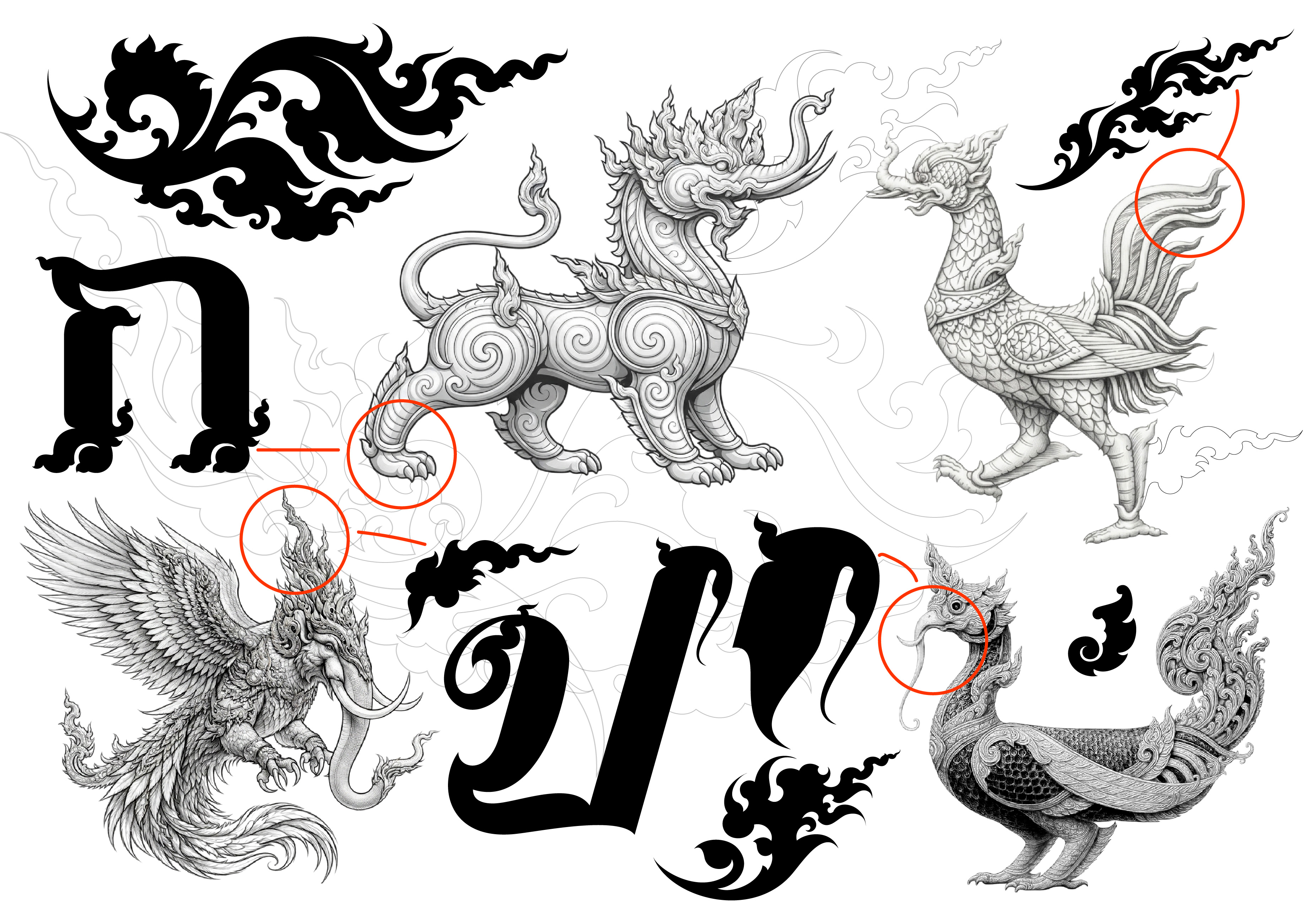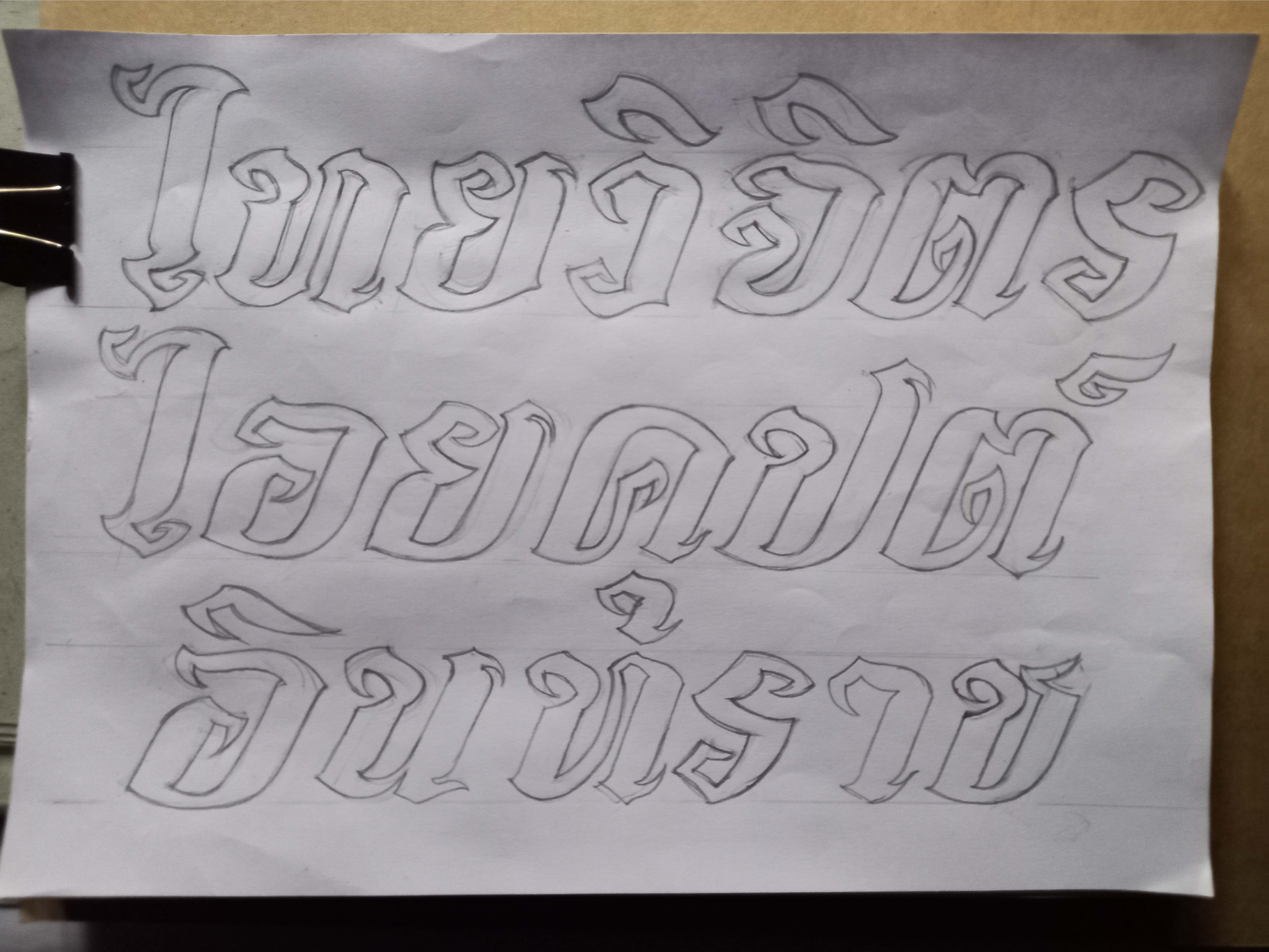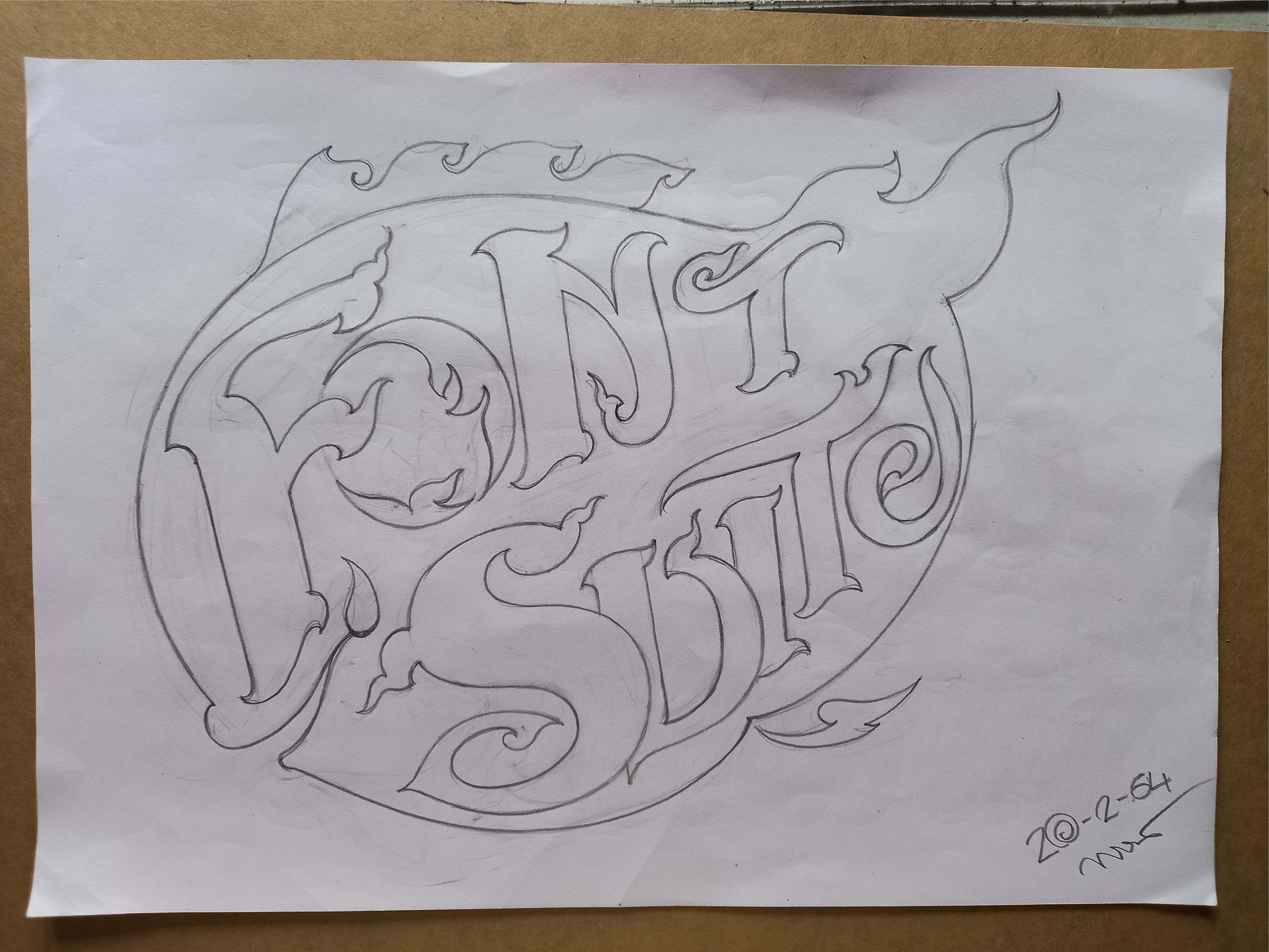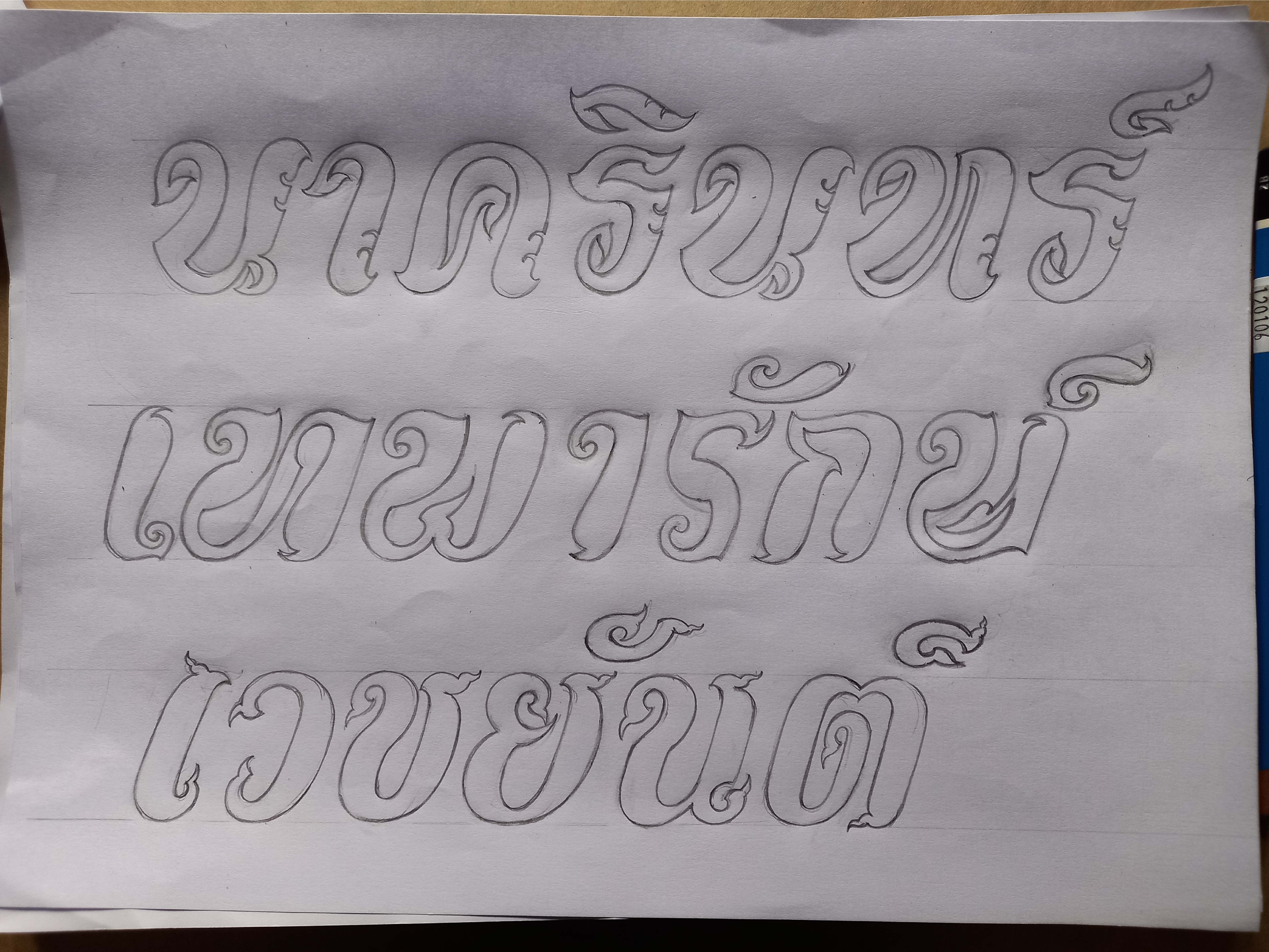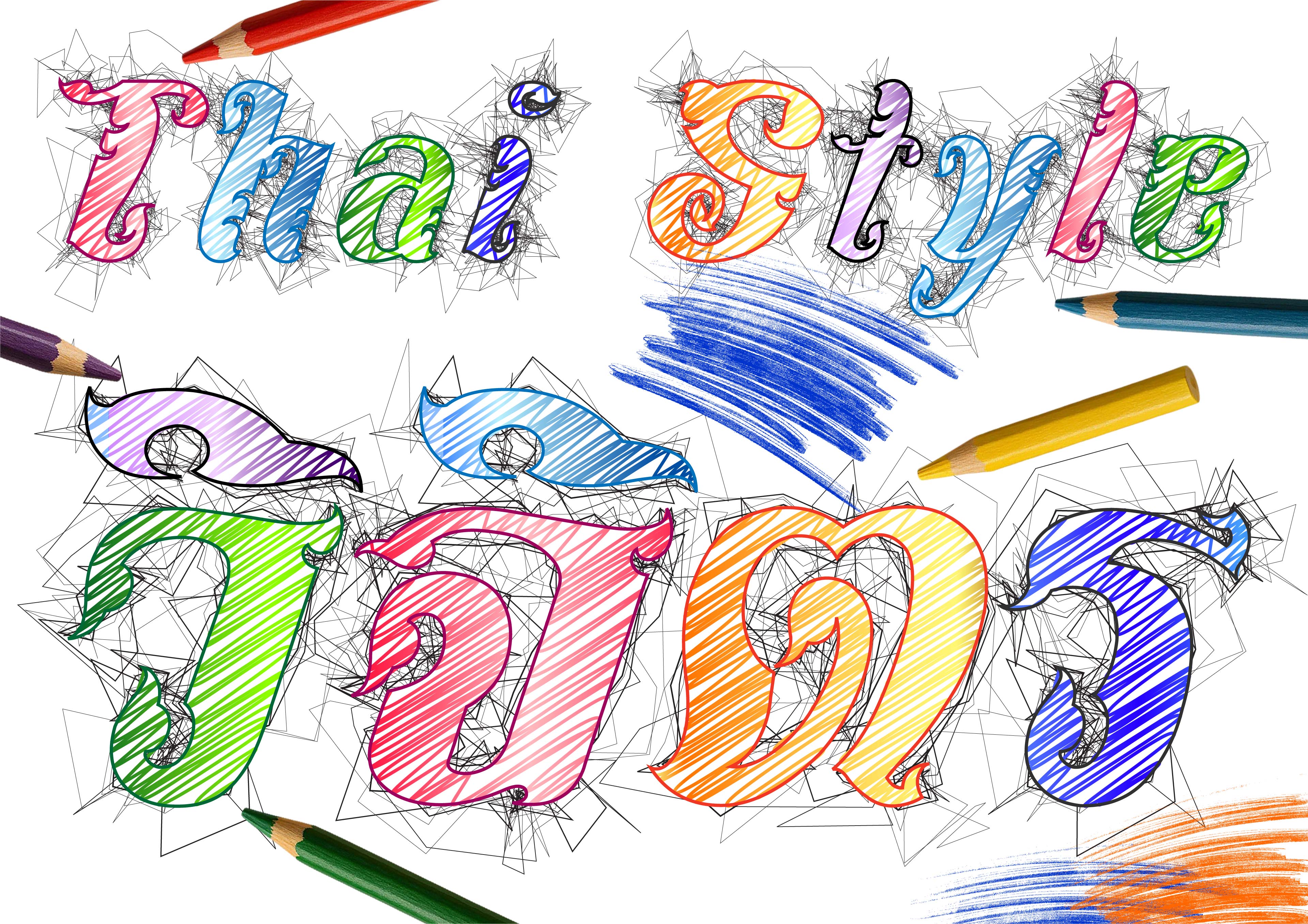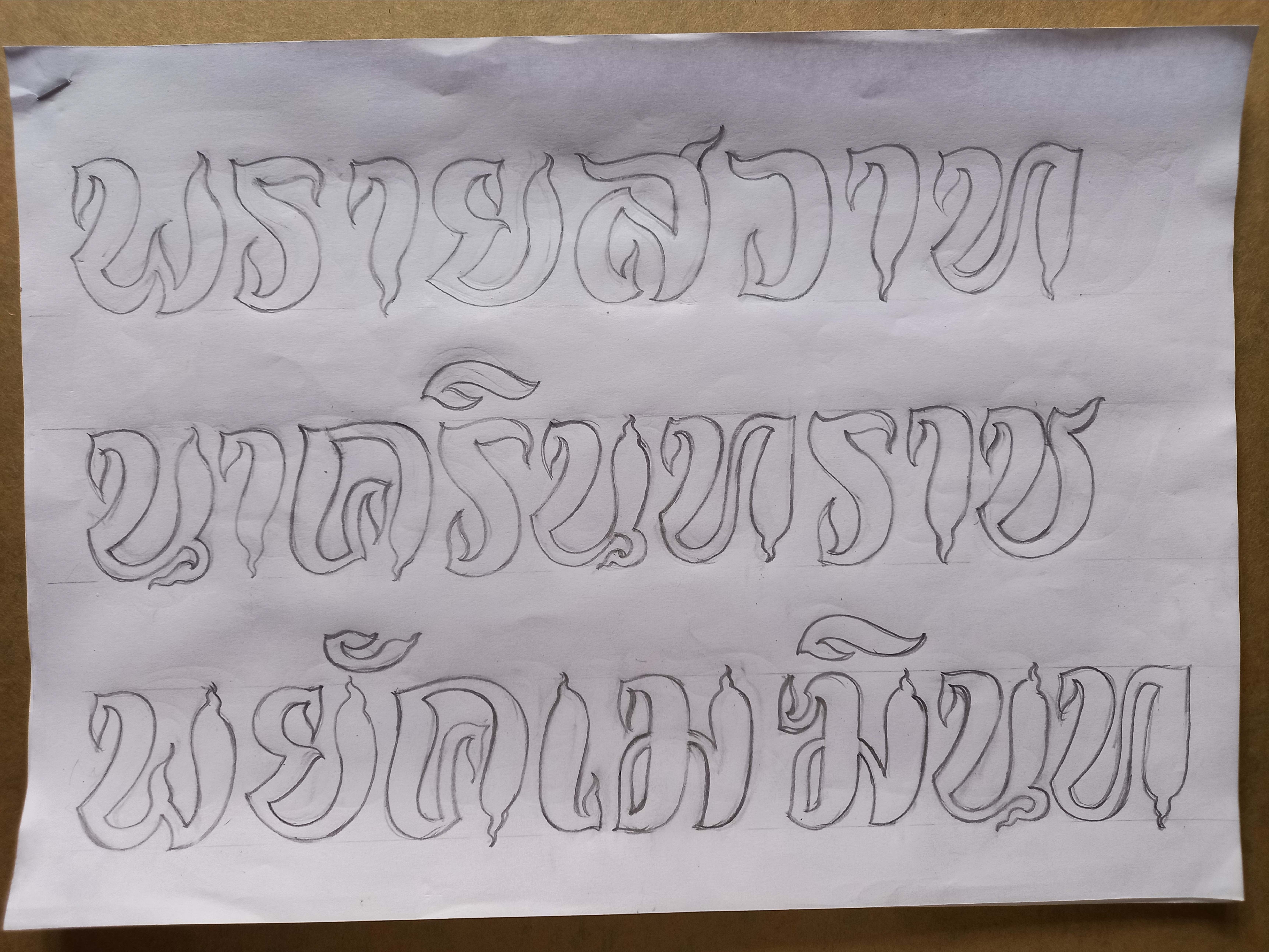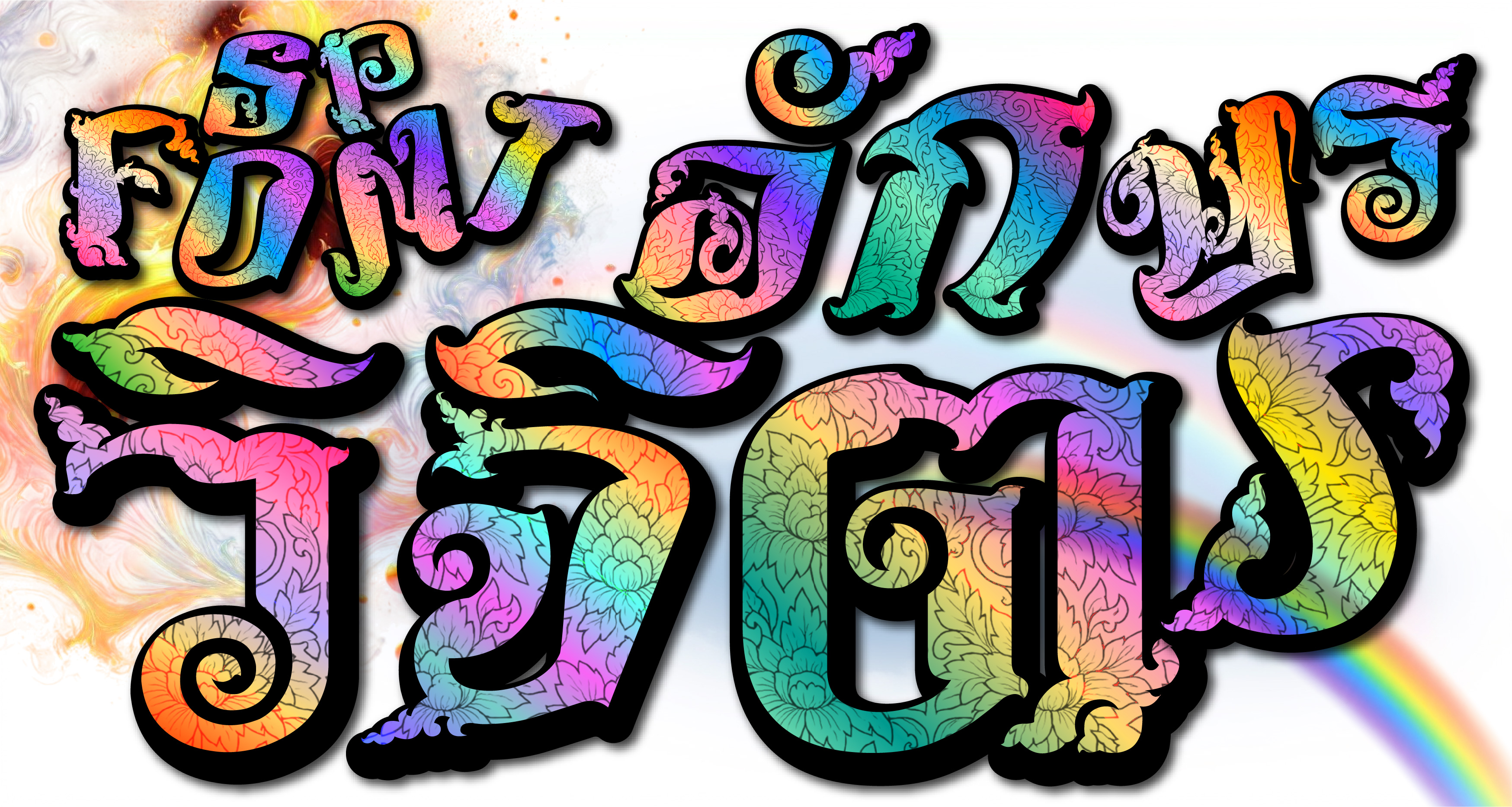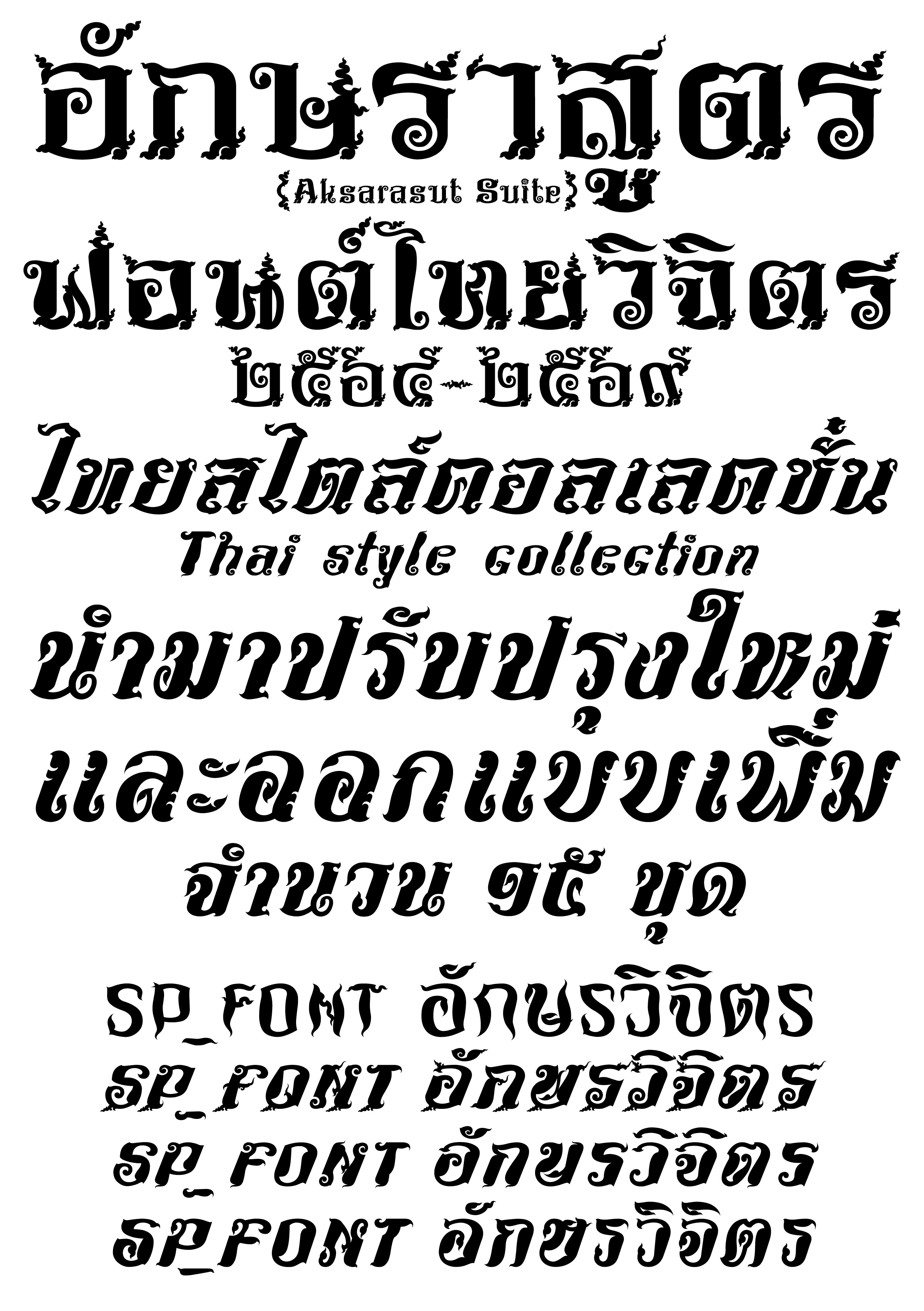
อักษราสูตรกับไทยวิจิตรฟอนต์
ไทยวิจิตรอักษราสูตร
จุดเริ่มต้นจากนกหัสดีลิงค์
นกหัสดีลิงค์ หรือหัสดิน แปลว่า นกตัวใหญ่ที่ส่วนหัวเหมือนช้าง มีพละกำลังเท่ากับช้าง 5 เชือก
ถ้าเป็นเครื่องยนต์ ก็หลายสิบแรงม้า สามารถถลาโฉบลงจับช้างแล้วบินขึ้นไปบนอากาศได้อย่างชิวๆ
ซึ่งนกนี้มีปรากฏอยู่ในพระไตรปิฎก คัมภีร์ทางพระพุทธศาสนา เรื่อง "พระเจ้าอุเทน" (หาอ่านได้ครับ)
เมื่อพระพุทธศาสนาเผยแผ่ลงมายังสุวรรณภูมิอาณาจักรล้านนา คัมภีร์พระไตรปิฏกถูกแปลบันทึก
เป็นภาษาล้านนาด้วย ผสมผสานกลมกลืนไปกับความเชื่อของผู้คน กลายเป็นวัฒนธรรมและตำนาน
กอร์ปกับสมัยนั้น เป็นยุคสงครามสู้รบแย่งชิงปกป้องแผ่นดิน เมื่อมีการฆ่าฟันกัน ก็มีการบาดเจ็บล้มตาย
เป็นจำนวนมาก ไม่มีเตาเผาไฟฟ้าดังเช่นปัจจุบัน อาศัยนำไปทิ้งลงหุบเหวบ้าง โยนลงน้ำบ้าง ขุดดิน
หลุมใหญ่แล้วฝังกลบบ้าง เมื่อมัวแต่สู้รบปรบมือ จะหาคนหาเวลาที่ไหนไปทำทัน อีกานกแร้งก็มารุม
ทึ้งสาวไส้กิน ไม่เว้นแม้แต่สุนัข แต่เมื่อสงครามจบ ก็มีเวลาไปนับศพทหาร ประกอบทำพิธีตามความเชื่อ
สำหรับเชื้อขุนมูลนายเจ้าฟ้ามหากษัตริย์ที่ทรงออกรบเอง หากสวรรค์คตลง ก็จะมีพิธีการปลงพระศพ
ให้สมพระเกียรติ ด้วยคติที่ว่าสัตว์ในเทพตำนาน ก็คือนกหัสดีลิงค์นี่เอง ที่มีเรี่ยวแรงมหาศาล จะสามารถ
นำพาวิญญาณของผู้ตายพวยพุ่งมุ่งทยานบินไปสู่สวรรค์ชั้นฟ้าได้สำเร็จสมประสงค์ จึงมีการสร้างหุ่นจำลอง
นกหัสดี ประดับประดาตกแต่งสีสันลวดลายให้วิจิตรพิสดารงดงามตระการตา บนหลังนกจะสร้างบุษบกโลงแก้ว
ไว้บรรจุพระบรมศพ ความเชื่อนี้ภายหลังต่อมาปัจจุบัน ยังคงมีให้เห็นบ้าง สำหรับพระสงฆ์บางรูป ที่ชาวบ้าน
เคารพนับถือ (ครูบา) ซึ่งการจัดทำพิธีแบบนี้ ต้องอาศัยความร่วมแรงร่วมใจของชาวบ้าน ช่วยกันสละเงินทอง
เพื่อนำมาเป็นทุนจัดสร้างนั่นเอง เป็นที่มาของคติธรรมเนียมประเพณีว่าด้วยปราสาทนกหัสดีลิงค์
แต่ถ้าพูดตามความเป็นจริงไม่อ้างอิงความเชื่อ (อันนี้ สายมูมีเคือง) นกหัสดีลิงค์ เป็นสัตว์ใหญ่ประเภท
ในยุคไดโนเสาร์ เป็นนักล่าเหยื่อเหมือนเหยี่ยว มีสายตาและกรงเล็บแหลมคม มองเห็นในระยะหลายร้อยลี้
มองเห็นช้าง ยังกับนกเห็นหนอน มันอ้วนท้วนดิ้นดุ๊กดิ๊ก ช่างน่ากินเหลือเกิ้น (โอ้ย..น้ำลายจะไหล..ไม่ไหวแล้ว)
ว่าแล้วก็ร่อนลงด้วยลีลานักบินระดับทีมชาติ กางปีกถลาลงเยื้องลีลาโฉบฉวัดแล้วจับด้วยกรงเล็บอันแม่นยำ
พร้อมใส่เกียร์นก โผผินบินขึ้นอากาศ เข้าไปในป่า วางช้างหนอนน้อยไว้บนคาคบไม้ ถ้าอยากหม่ำในตอนนั้น
ก็ใช้เท้ายันไว้พร้อมใช้จะงอยปากจิกลงไป ดึงออกให้พอดีคำ กลืนเนื้อนุ่มๆชุ่มปากลงไปในลำคอ...หวานเจี๊ยบ
สัญชาตญาณของนกนักล่า ย่อมจะต้องกินของสดที่เป็นๆอยู่ เนื้อยังดิ้นเลือดพลุ่งพล่านถึงจะอร่อย ส่วนสัตว์ที่ตาย
ก็เหมือนกับเนื้อแช่เย็น ขาดรสชาติ ไม่เป็นที่เร้าใจของอารมณ์ อาจทำให้ร่างกายขาดสารวิตามินได้ (รักสุขภาพ)
คนตายก็เช่นกัน เมื่อเริ่มจะเน่าเหม็นเพราะหนอนชอนไช ก็หวานคออีแร้งได้ทั้งเนื้อทั้งหนอนเหมือนปลาร้าส้มตำ
(ของชอบอยู่ที่คนมัก)  ส่วนที่ปากนกเป็นงวงช้าง ก็ตอนมันบินขึ้นต้องใช้ปากจิกช่วยไม่ให้เหยื่อดิ้นหลุด คนมอง
เห็นอยู่ไกลๆก็เข้าใจว่ามีปากเหมือนช้างไม่งั้นจะจิกกินเนื้อได้ไง ไม่ได้กลืนเหมือนอ้อยซักหน่อย
ความเชื่อของคน ถ้าเป็นศพของผู้มีบุญญาวาสนาบารมี ก็อยากจะใช้นกที่มีระดับชั้นดีหน่อยไม่ใช่อีแร้งอีกา
ตัวเล็กๆ ต้องใช้นกหัสดีเท่านั้นถึงจะเหมาะสม ทำการดัดนิสัยเดิม แทนที่จะจับก็กลับมาบรรทุกแทน ให้ดูดีว่างั้น
แถมไม้ใช่เนื้อที่ดิ้นอยู่ ไปส่งแค่เชิงตะกอน ไม่ได้บินขึ้นฟ้าด้วยซ้ำ ถูกเผาไปด้วยเลย
ถ้าเป็นขั้นความจริงสูงสุดละก็ จิตวิญญาณนั้น เป็นนามธรรม จับต้องหรือมองเห็นด้วยตาเนื้อไม่ได้ ไม่มีผู้ใด
สิ่งใด จะนำพาดวงจิตนั้นไปลงนรกหรือขึ้นสวรรค์ได้ จิตที่ประกอบกรรมดีและชั่วของผู้นั้น จะเป็นสิ่งนำพาไปเอง
เหมือนสวรรค์กับนรกไม่ได้มีใครไปขยายแยกชั้นแยกขุมให้มากมายได้ มีก็แต่เพียงจิตใจที่ดีงามหรือชั่วช้าเท่านั้น
ที่ไปขยายขุมนรกให้กว้างใหญ่ออกไปเอง และขยายชั้นฟ้าสวรรค์วิมานออกไปได้หลายชั้นนั่นเอง ฉะนั้นปราสาท
นกหัสดีลิงค์ ก็เป็นเพียงตำนานความเชื่อของปุถุชนคนทั่วไป
หากมองด้วยความจริง ความเชื่อก็หมดความศักดิ๋สิทธิ์ไป แต่ในที่นี้ จะอาศัยลวดลายศิลปะในตัวนกทำให้เป็น
เอกลักษณ์ของฟอนต์เท่านั้นนะครับ  (เรื่องนกยาวกว่าเรื่องทำฟอนต์-อ่านเอามัน)
โครงการนี้ เป็นการ Renovate ฟอนต์เก่า ปี 2021 ปรับปรุงรูปแบบให้ดูหล่อขึ้น พร้อมจัดช่องไฟ
ใส่ Options-Features ให้มันสมบูรณ์แบบ
ส่วนฟอนต์ชุดที่ทำเพิ่มใหม่ ลองดูซักตัวก่อนนะครับ